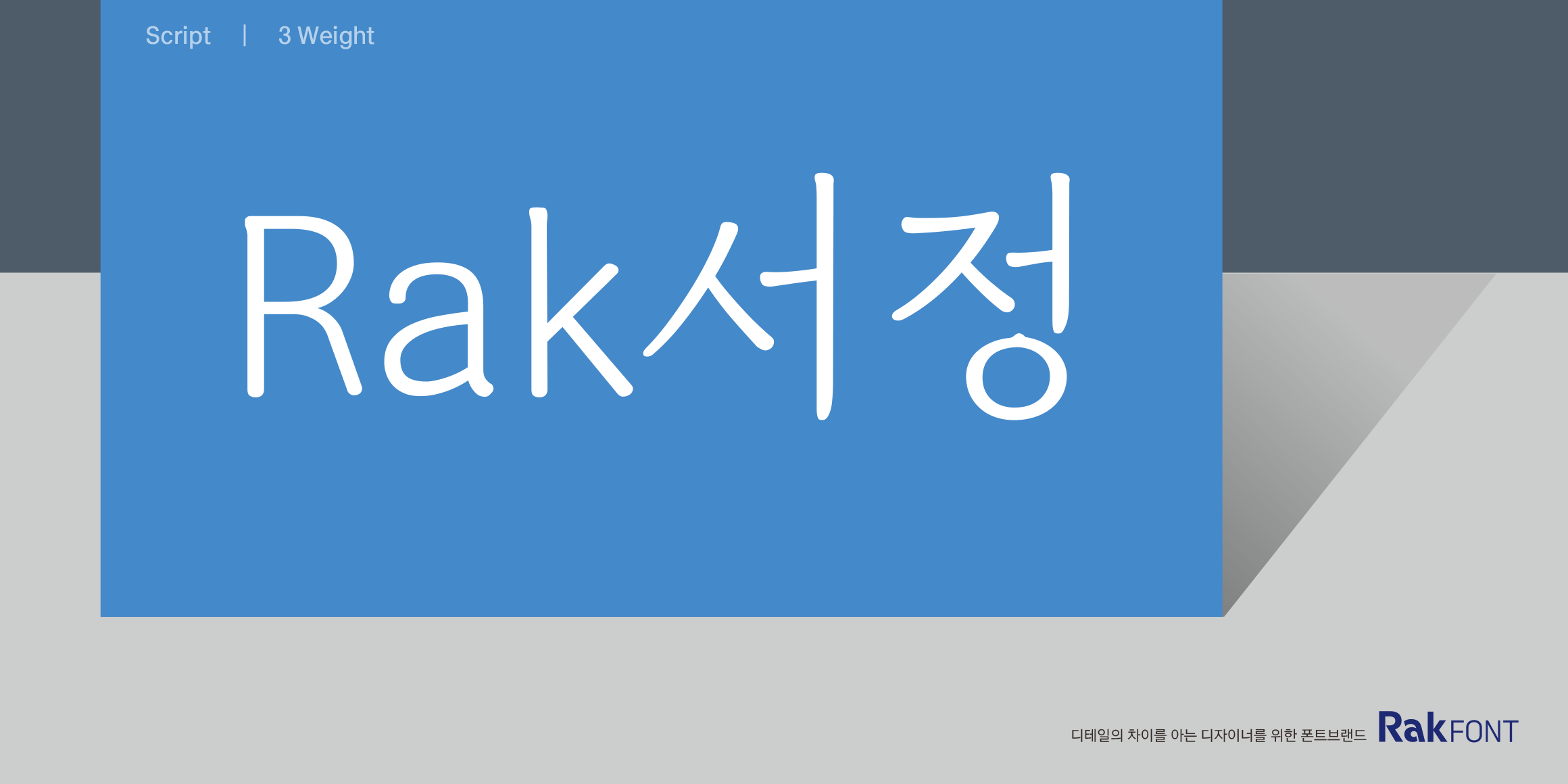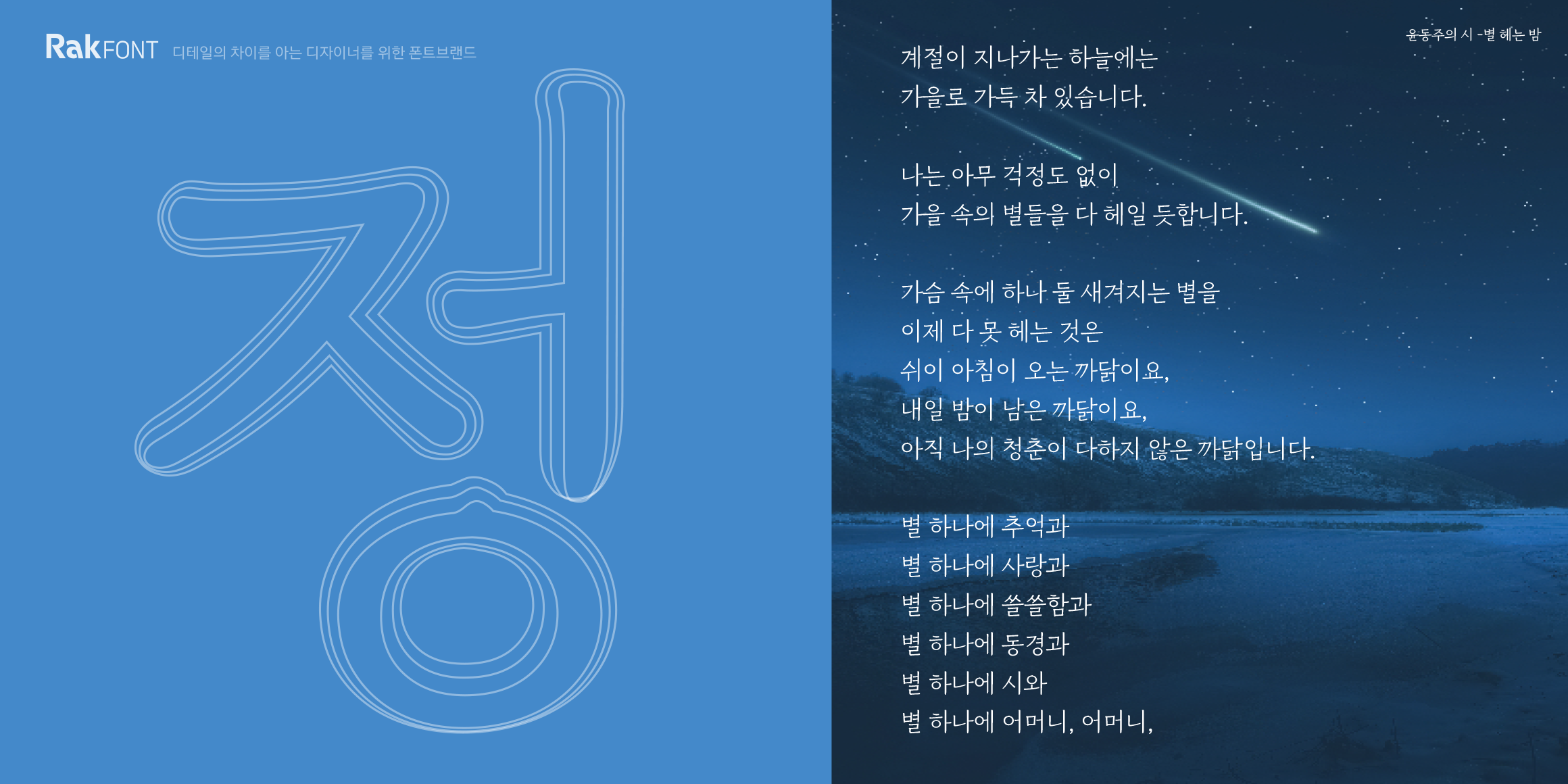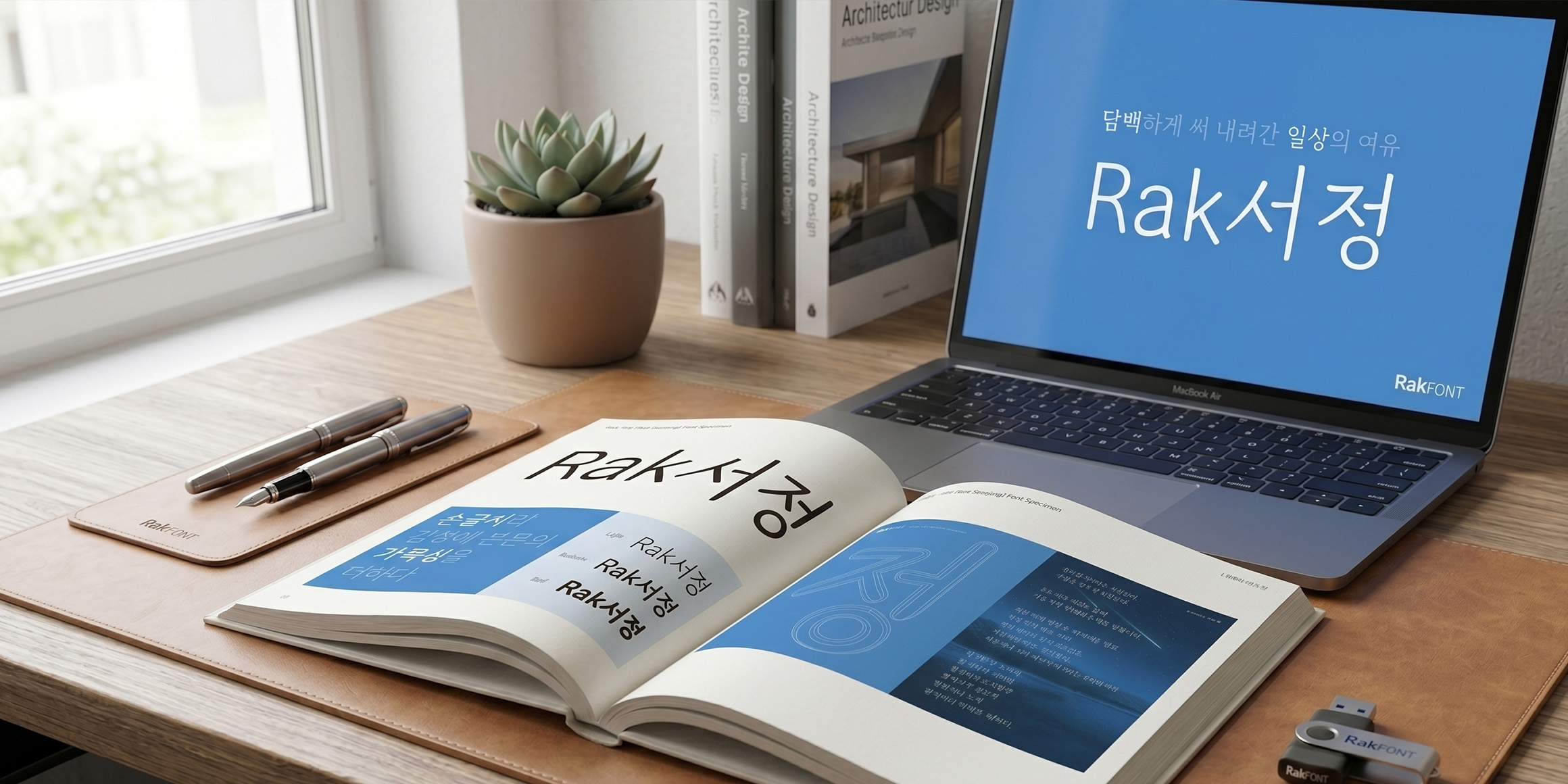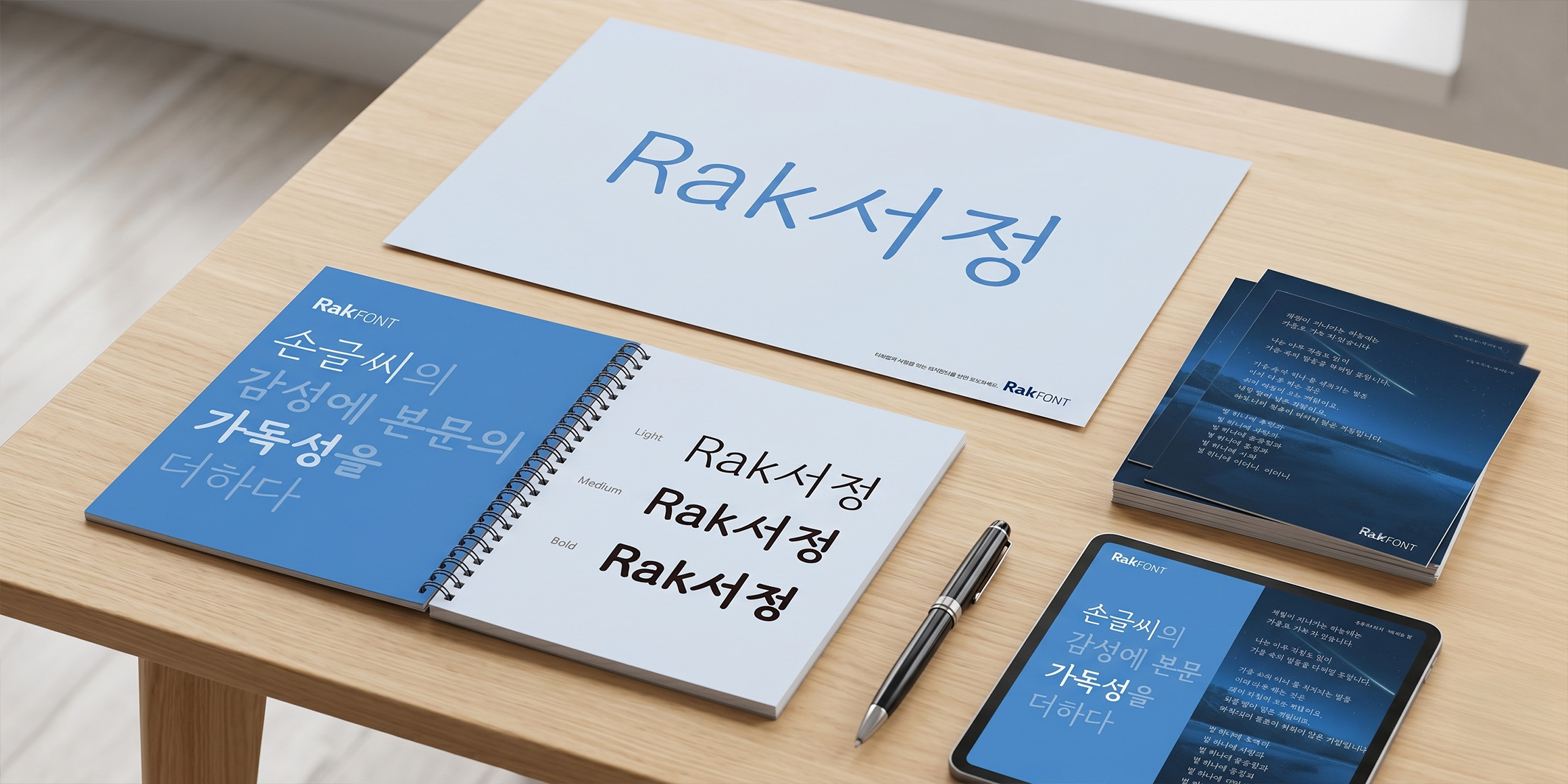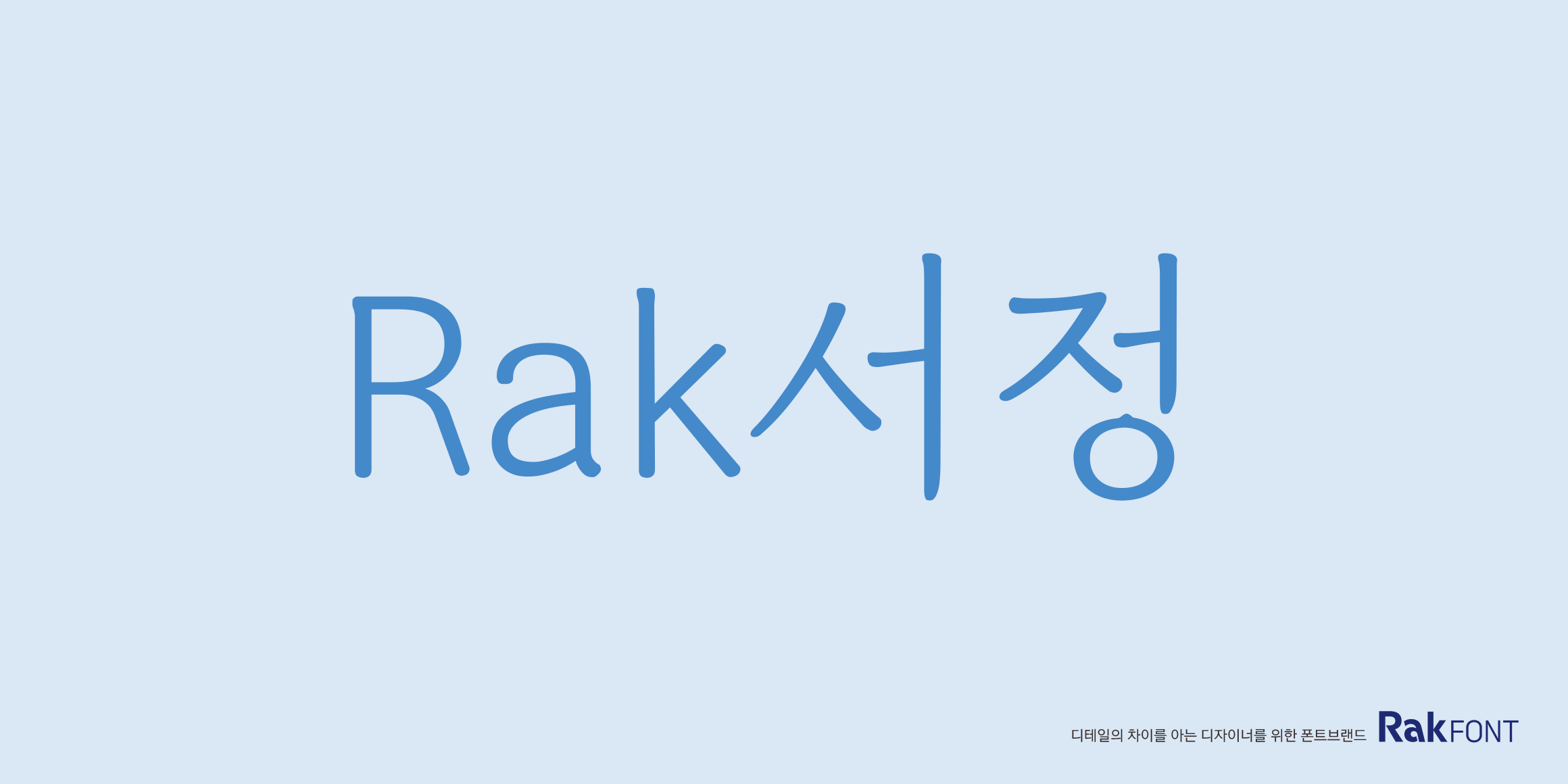
Rak서정
Rakfont
분류 Script,손글씨
기교를 덜어낸 순수한 형태가 돋보이는 'Rak서정'입니다. 손글씨 특유의 자연스럽고 여유로운 분위기를 자아내면서도, 글줄의 흐름을 정교하게 다듬어 짧은 호흡의 본문용으로도 손색이 없습니다. 꾸밈없이 진솔하고 따뜻한 메시지를 전달하고 싶은 모든 콘텐츠에 자연스럽게 스며듭니다.